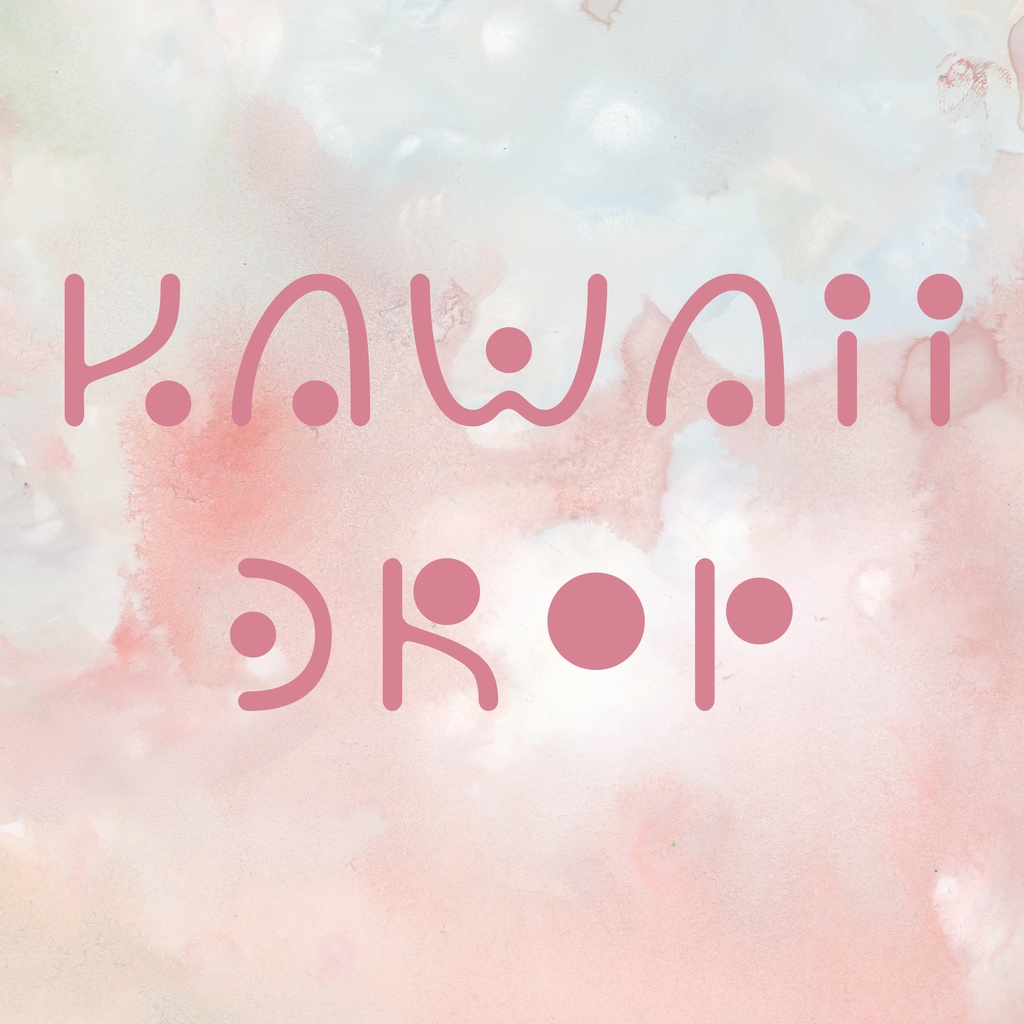
MochiFonts欧文フォント「Kawaii Drop」Digital500 JPYAdd to CartBuy a GiftAbout Giftシンプルな可愛さと、水滴のような美しさを兼ね備えたフォントです。小文字は入っていないので、caps lockをオンにして入力すると便利です。 収録内容: アルファベット大文字、数字、約物 データ形式:OpenType 商用利用:可能 禁止事項: 二次配布(転売)、自作発言、公序良俗に反する使用 著作権は製作者に帰属します。使用報告やクレジット表記は任意です。MochiFontsVisit FANBOX!